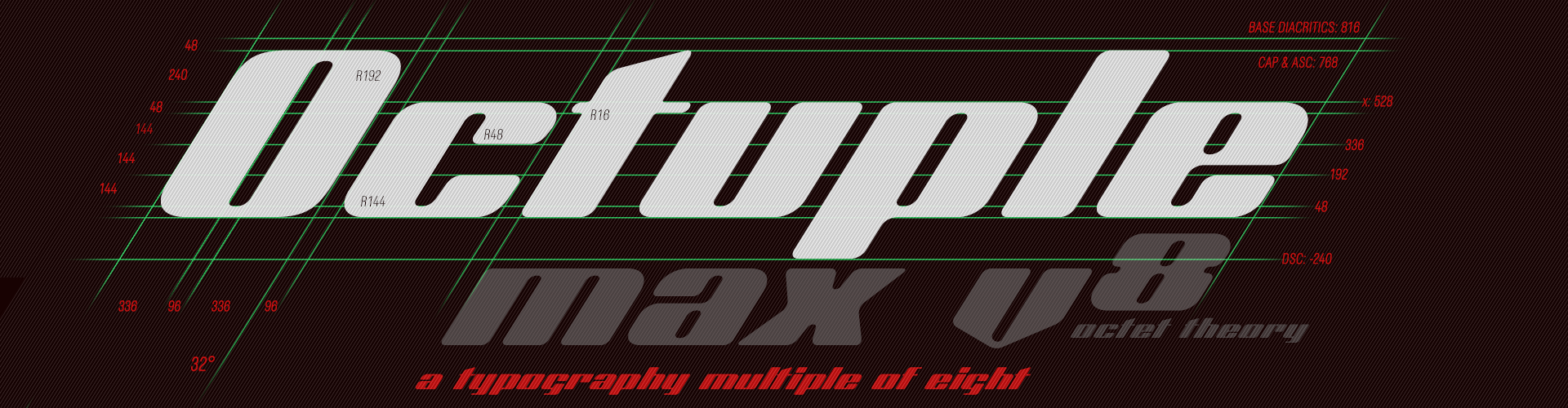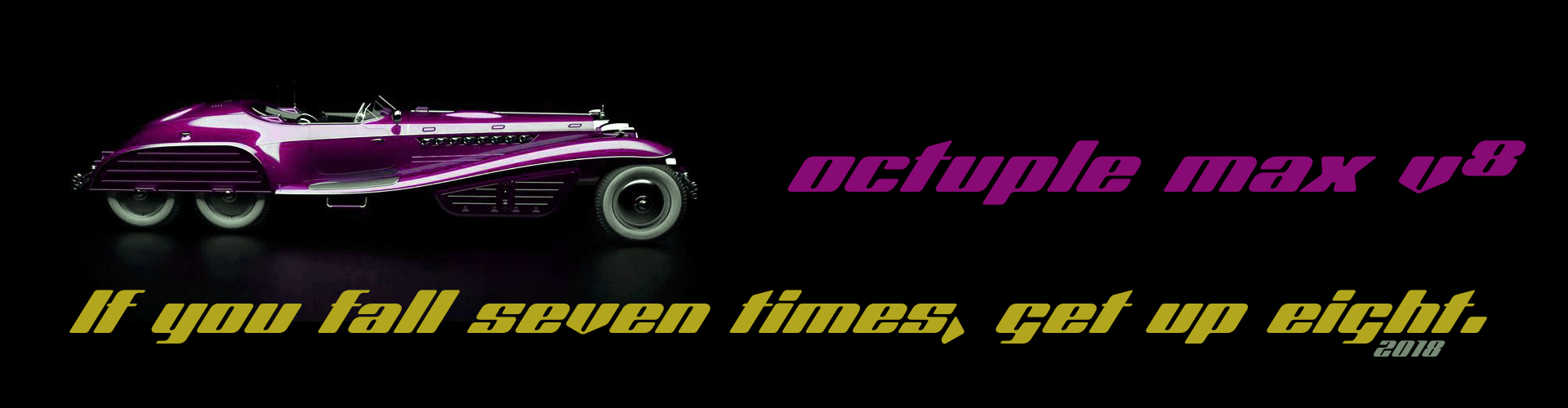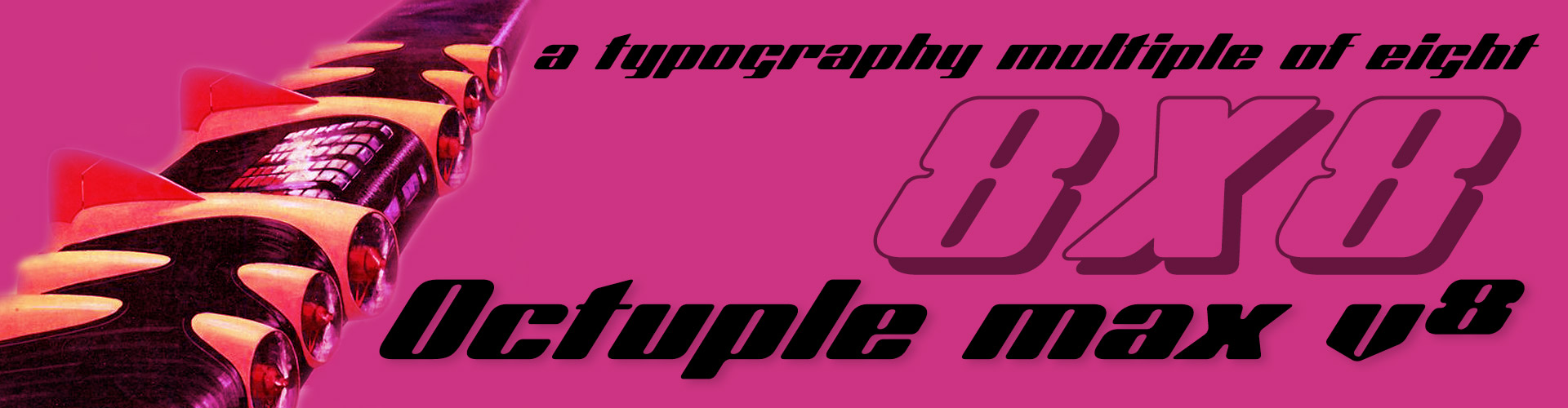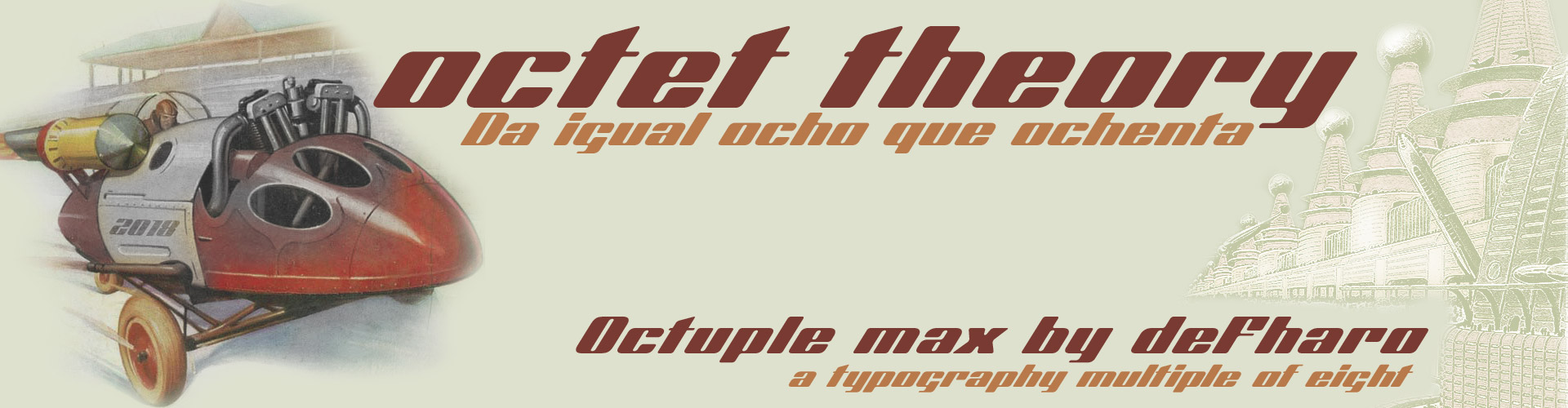
octet font theory
Estilo: Sans Serif, Cursive, Techno, Rounded
Proporción: Cursiva
Autor: deFharo
Funciones OpenType: Additional languages, All Alternates, Bitcoin, Contextual Alternates, Denominators, Discretionary Ligatures, Extended Fractions, Historical Forms, Inferiors, Kerning, Localized Forms, Numerators, Oldstyle Figures, Ordinals, Scientific Inferiors, Small Capitals, Standard Ligatures, Subscript, Superior letters, Superiors, Superscript.
Comencé con una inclinación de 32° para todas las letras, después construí una cuadrícula con divisiones horizontales de 48/unidades de altura, así definí la altura de la x: 48×11=528/u, la altura de las mayúsculas y ascendentes: 48×16=768/u, los descendentes: 48×4=192/u y la línea de base de los acentos diacríticos: 48×17=816/u.
La anchura de las astas verticales es de 48×7=336/u, las astas horizontales tienen una altura de 48/u, las minúsculas llevan una pequeña corrección óptica en las medidas de las astas verticales.
Las contraformas de los caracteres tienen todas una anchura de: 48×2=96/u lo que supone una anchura que siempre es múltiplo de ocho (336+96+336/8=768/u) observad que la anchura general de los caracteres con dos astas verticales es igual a la altura de las mayúsculas, esto hace que la proporción final de la tipografía sea cuadrada, con el gran aporte de la inclinación que rompe la rigidez y pesadez de una posible versión romana de esta fuente realizada con el mismo concepto de medidas.
También utilizo varias medidas múltiplos de ocho para el radio de los ángulos en las esquinas, dependiendo de la altura o de si estas son más o menos agudas, el más utilizado es el radio de 48/u. Otros radios que he utilizado para las curvas: 16, 24, 32, 96, 144, 192 y 240/u
En todo caso en el proceso de creación he disfrutado muchísimo por mi inclinación hacia el dibujo geométrico y las matemáticas, espero que esta tipografía de estilo neo-retro guste y se utilice para cualquier tipo de diseño publicitario, carteles, películas o allí donde se busque una tipografía con personalidad propia.
Octuple max dispone de soporte completo para todos los idiomas derivados del Latín (Latin Extended-A)y funciones OpenType avanzadas para numerales, fracciones, ordinales, etc.